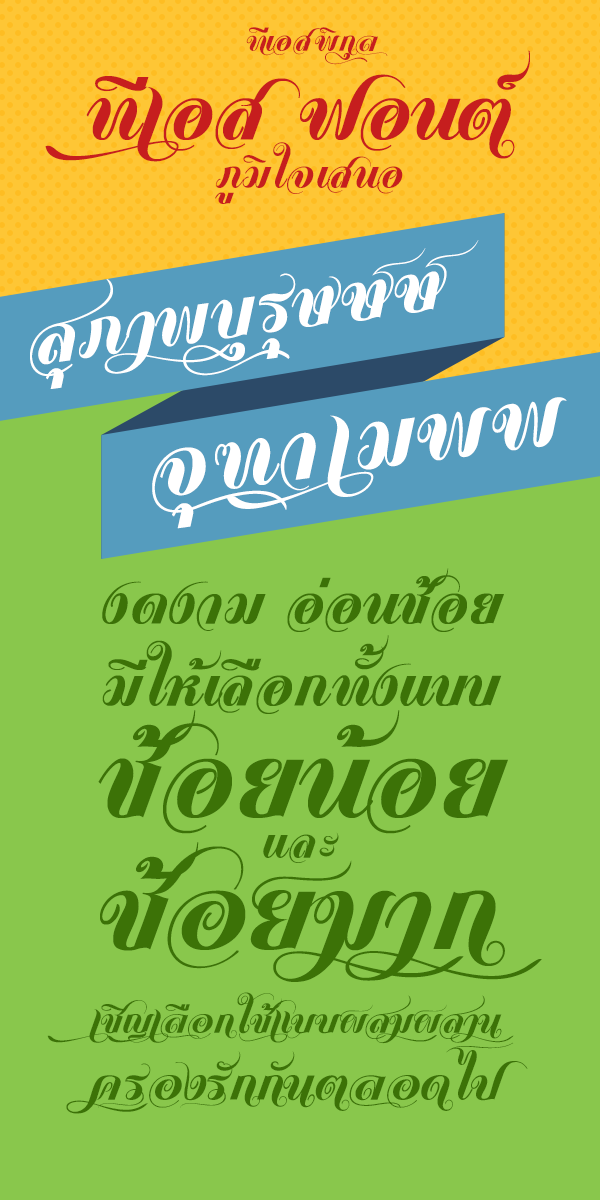
TS-Phikun NP
ฟอนต์ใหม่จากยอดฝีมืออาจารย์ธงแห่ง TS Font เจ้าของเดียวกับ TS-SOM TUM-NP (ส้มตำ) ที่เป็นที่ฮือฮาในความแซบสะเด่าทรวง คราวนี้มาแบบอ่อนช้อยงดงามแต่หรูหราอลังการตามอารมณ์กวี ฟอนต์นี้อาารย์ธงได้เล่าถึงที่มา ว่าได้รับแรงบันดาลใจมาจากบทกวีของท่านอังคาร กัลยาณพงศ์ ศิลปินและยอดกวีในตำนานท่านหึ่งของเมืองไทยผู้ล่วงลับไปแล้ว
ภายในฟอนต์ชุดนี้ คุณสามารถปรับเปลี่ยนรูปแบบของตัวอักษรได้ทั้งแบบช้อยมาก และช้อยน้อย ด้วยการปรับจาก Italic เป็น Bold Italic ครับ ลองนำไปประยุกต์ใช้ดู แต่ดูแล้วฟอนต์นี้น่าจะดูหรูหราอลังการ เหมาะกับงานฉลองมงคลสมรสดีนะครับว่าไหมเอ่ย
ทำไมต้องมีตัวปกติและตัวไม่ปกติ จุดประสงค์ของการออกแบบฟอนต์ที่มีสองชุด ซึ่งจะแสดงเป็นตัวหนาหรือตัวอะไรก็ตาม ที่สองแบบคือแบบปกติมันก็ปกติ เออ งง แล้วอีกตัวที่มันไม่ปกติ ก็มันไม่ปกติ (เขียนเองงเองแล้ววะ จะมีใครเข้าใจมั้ยนี่) เอาไงดีวะ ก็ไอ้ตัวที่เสริมมา ที่มีชื่อเดียวกันและส่วนมากหางยาวๆ นะ เช่น Phikun italic คู่กับ Phikun Bolditalic ถ้าเอาตัว Phikun Bolditalic ไปใช้เป็นตัวเนื้อทั้งหมด มันอาจทำให้งานเลอะได้ แย่งกันเด่นดูแล้วสะเหร่อครับ ผมต้องการเอามาเสริมตัวปกติให้ดูน่าสนใจขึ้น เช่นแทนตัวนำหน้า หรือห้อยท้าย และอาจต้องขยับช่องไฟใหม่บางตัว (ผมตามเก็บไม่หมด สองแบบรวมกันมั่วจนมึนตึ๊บเลยครับท่าน) ตามแต่เห็นสมควรประมาณนี้ครับ ผมเองก็เจอปัญหาลุกค้าเห็นปั๊บ เอาแบบนี้เลย แฮ.. ทำไงดีละชื่อบ่าวสาวหางพันกันนัวเนียอายเขาตายเลย แต่เขาชอบนะ ปลูกบ้านตามใจผู้อยู่ก็แล้วกัน ทีนี้ก็อยู่ที่จะเลือกใช้แล้วว่าจะทำกับมันยังไง.. และก็ไม่ควรไปดึง ไปยืดให้มันสูงโย่ง ทำให้ดูแล้วแปลกๆ เพี้ยนๆ เหมือนผู้เขียน แล้วผมจะทำต่อดีไหม ทำแล้วได้อะไร อ๋อไม่ได้ ก็ไม่เป็นไร ถ้ามันใช้ได้และได้ใช้มันก็คุ้ม